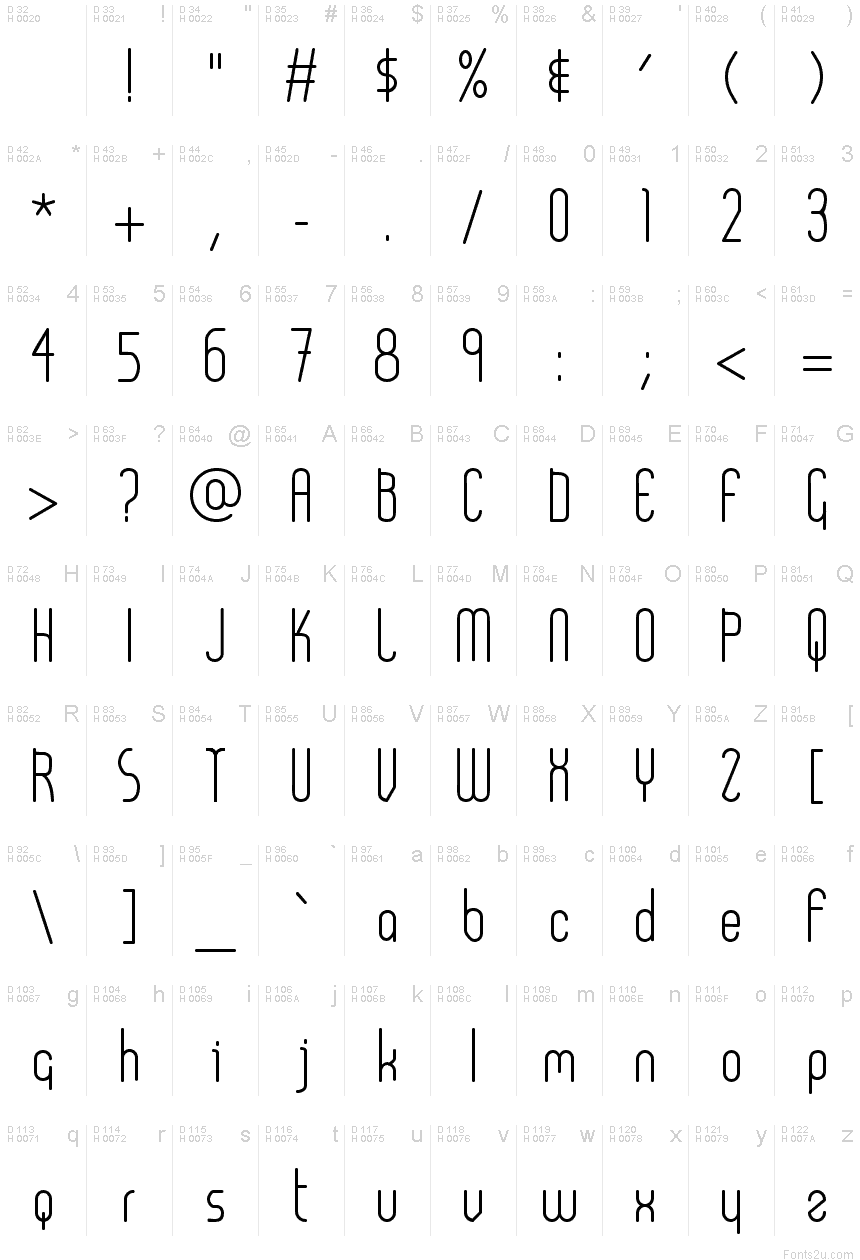
AB UltraChic, zaprojektowany przez Amita Botre, to darmowy krój display w stylu retro, zbudowany z wysokich, wąskich znaków oraz gładkich, jednoliniowych pociągnięć. Zaokrąglone łuki i długie linie pionowe nadają liternictwu elegancki wygląd w stylu magazynów modowych z lat 60., oparty na powściągliwych krzywiznach i oszczędnej, geometrycznej konstrukcji.
Plakat modowy to dla niego najbardziej naturalne zastosowanie, ponieważ wydłużone formy nawiązują do winiet czasopism vintage oraz brandingu marek haute couture. Krój sprawdzi się również na opakowaniach kosmetyków, szyldach butików i okładkach magazynów, gdzie litery mogą stać się częścią pasiastej ilustracji architektonicznej zamiast zwykłego tekstu.